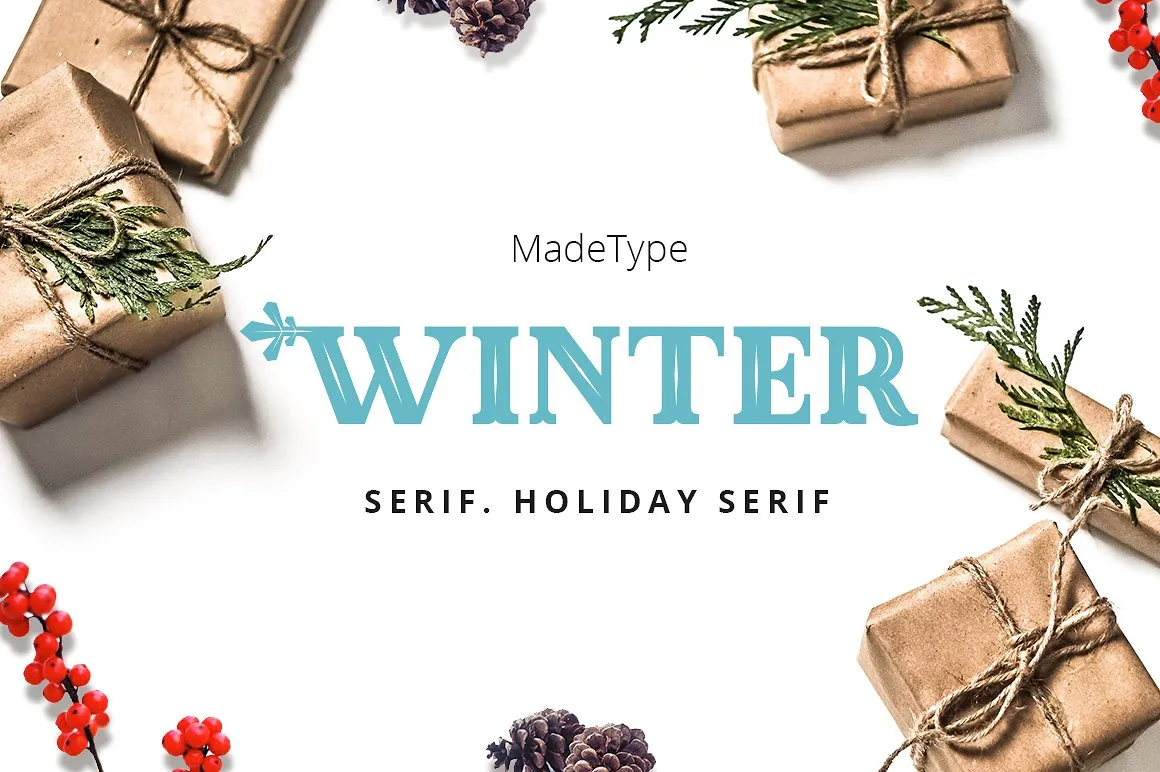
MADE Winter Typeface – Download Grátis
Introduzimos a MADE Winter Typeface. Desenhada pelo MadeType, ela surge no momento de renovação do novo ano. Inspirada na atmosfera festiva e projetada para seus trabalhos futuros que você deseja fazer com gosto. Perfeita tanto para headlines quanto para textos curtos, cartões postais, calendários, revistas, livros e até mesmo para logotipos. Experimente-a agora!